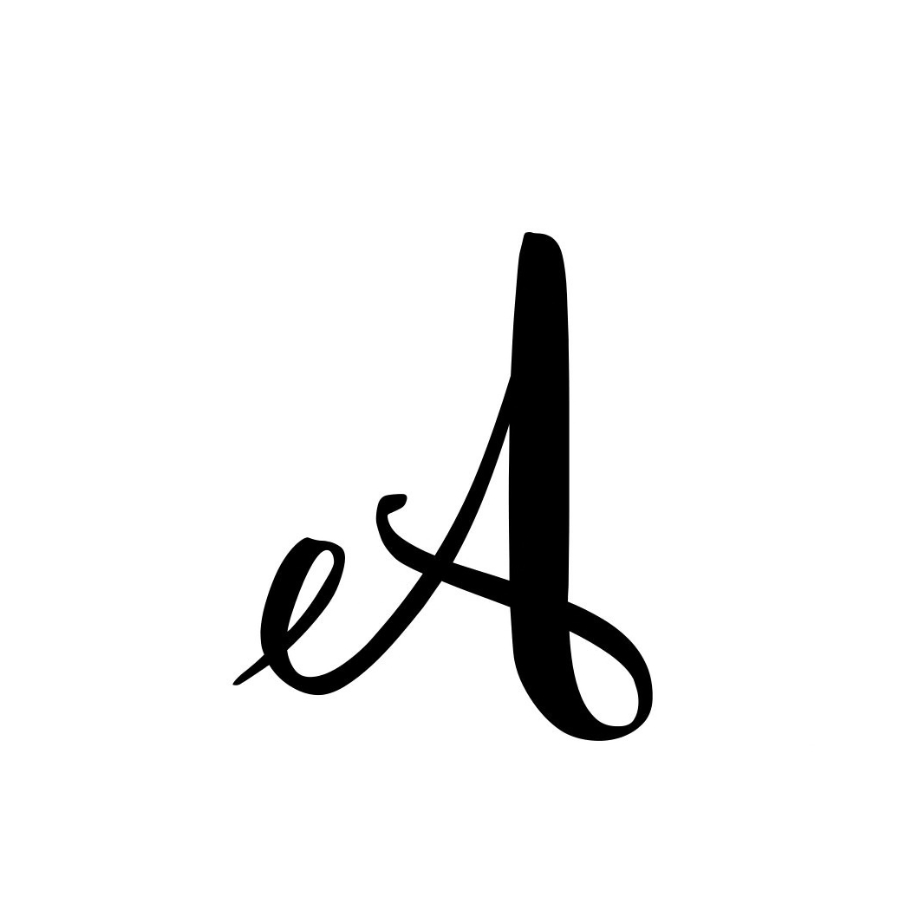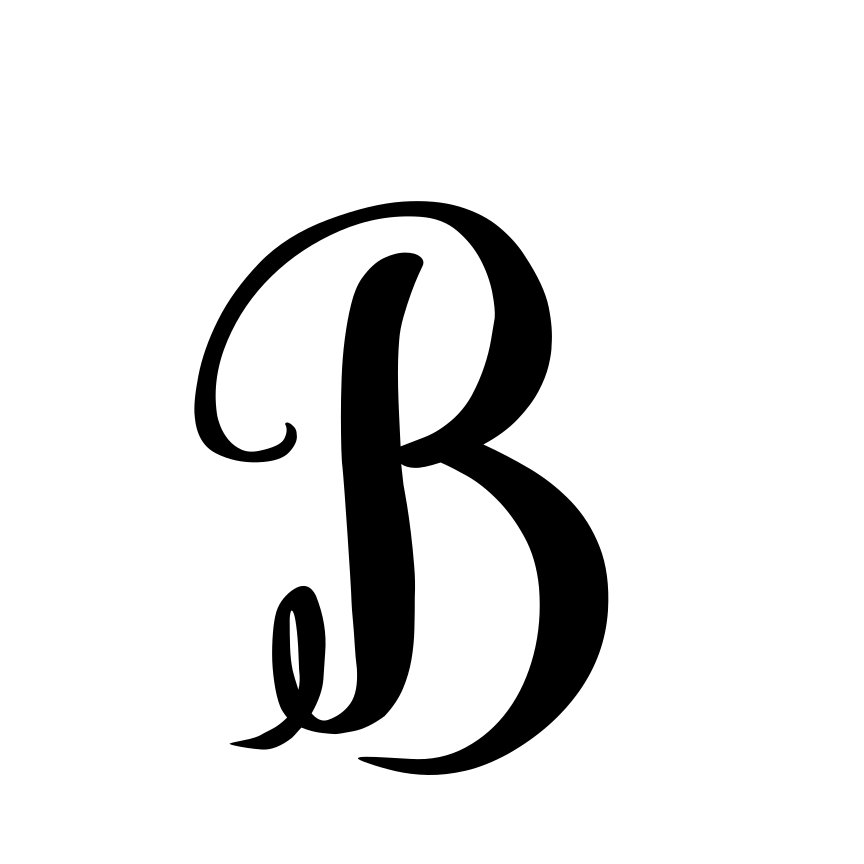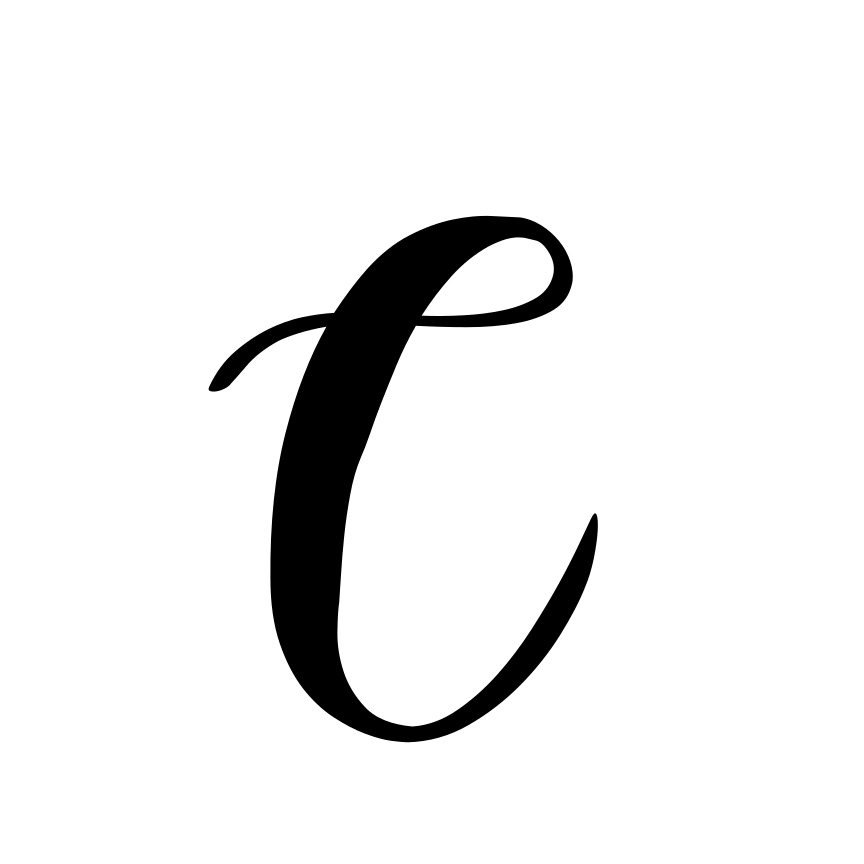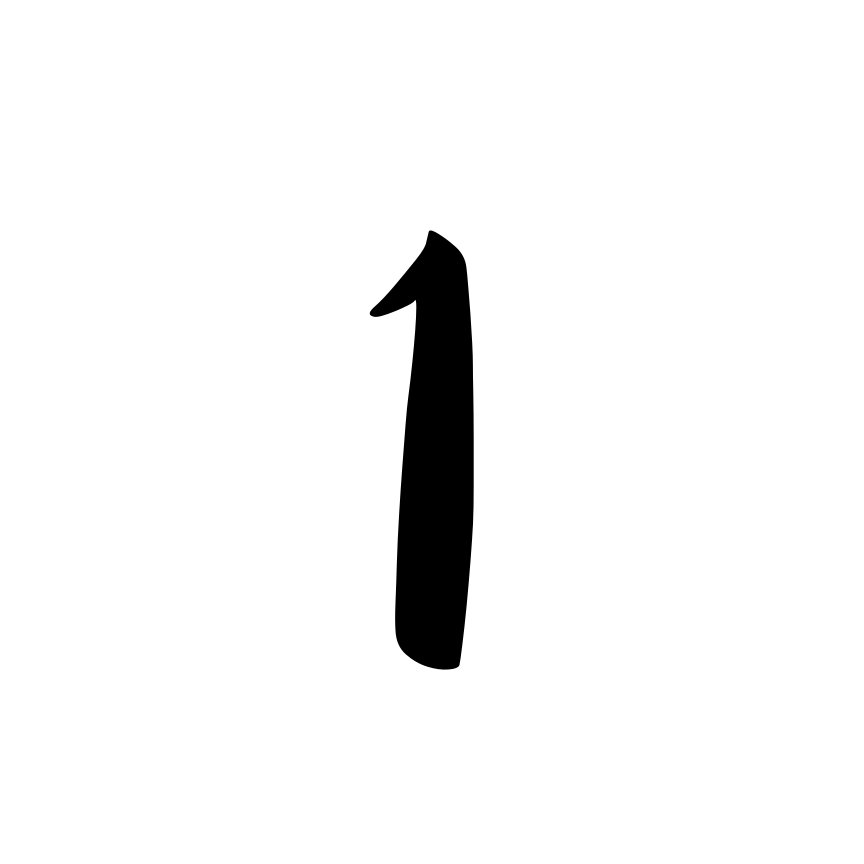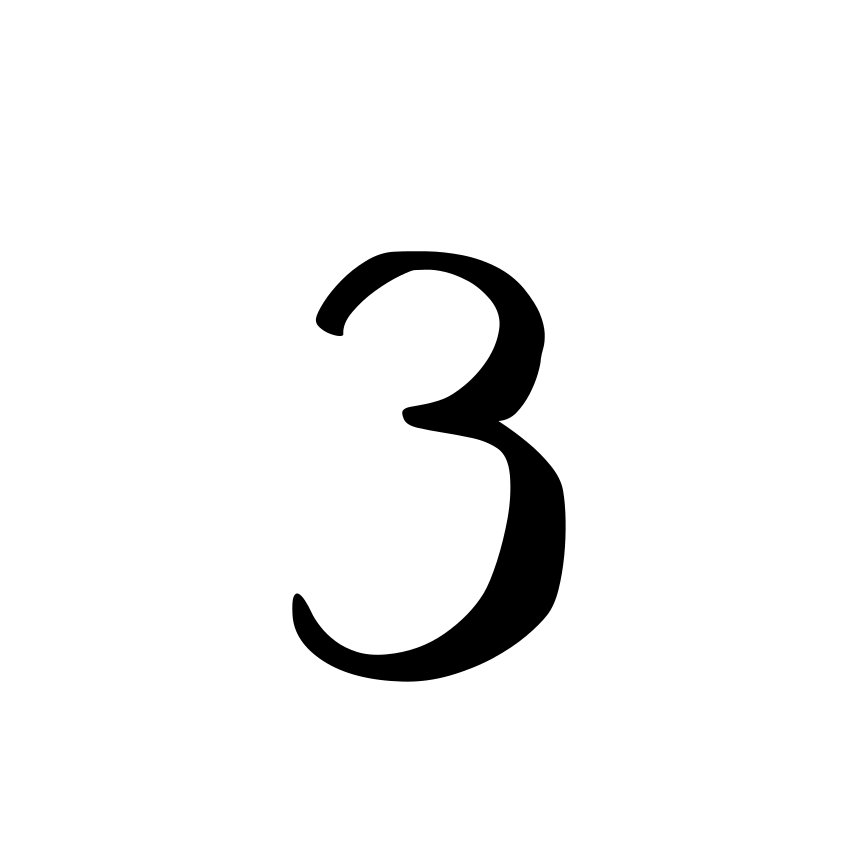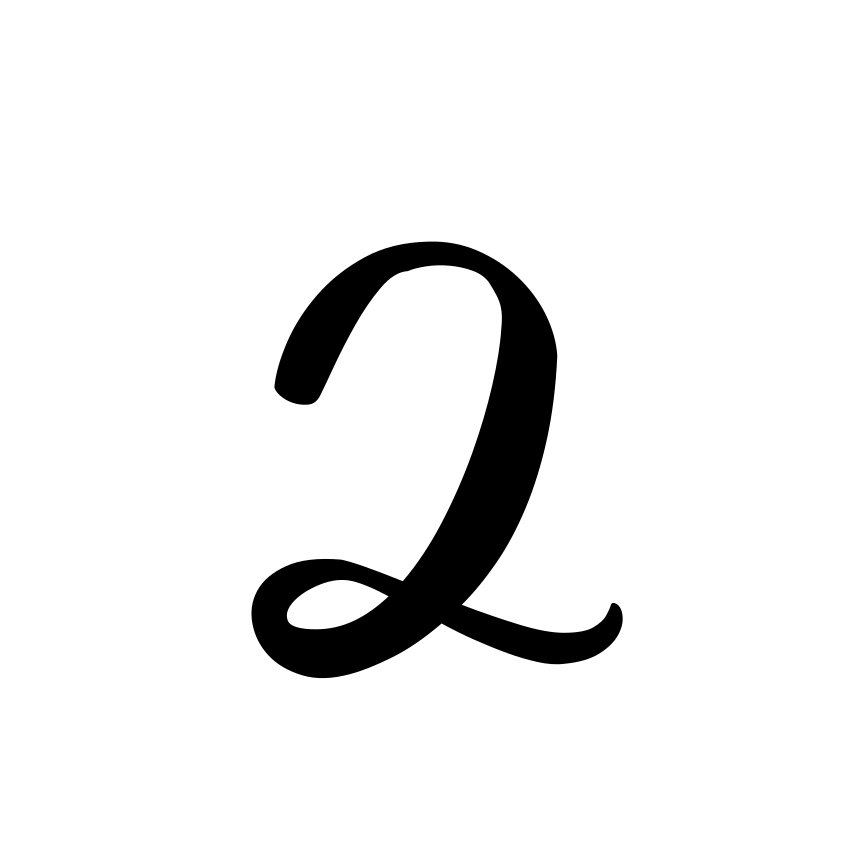
Die Winter Magic Monogramm Schriftart ist eine dekorative Script-Schrift, inspiriert von magischen Wintergeschichten und festlichen Dekorationen. Die Buchstaben besitzen fliessende Kurven, verspielte Formen und elegante Schwünge, die dem Text eine besondere Leichtigkeit und einen charmanten Charakter verleihen, während die Schrift gleichzeitig gut lesbar bleibt.
Die Schrift enthält Grossbuchstaben, Kleinbuchstaben, Zahlen sowie Satzzeichen. Die Grossbuchstaben eignen sich besonders gut für elegante Monogramm-Designs, während die Kleinbuchstaben denselben weichen und verspielten Stil beibehalten und so harmonische Wörter, Namen und dekorative Schriftzüge ermöglichen.
Die Winter Magic Monogramm Schriftart eignet sich ideal für kreative Bastelprojekte, personalisierte Geschenke, saisonale Dekorationen, Grusskarten, Etiketten und Vinyl-Designs. Ihr eleganter Script-Stil passt perfekt zu Initialen, Namen und stilvollen Monogramm-Layouts und ergänzt gleichzeitig winterliche Themen und kreative Schriftgestaltungen.